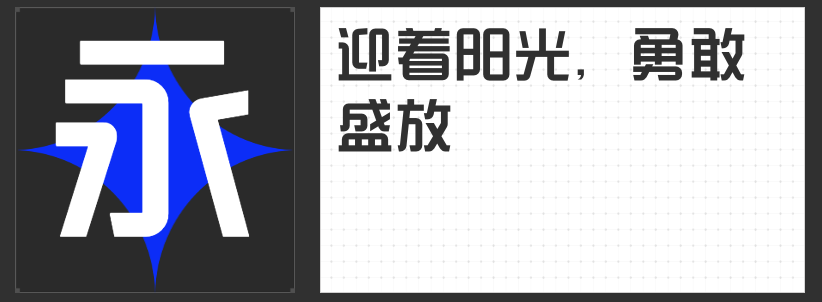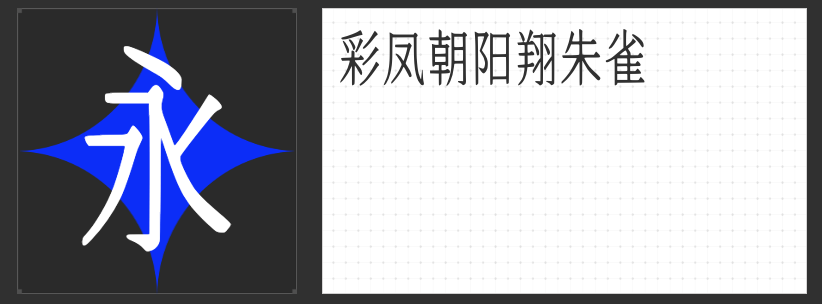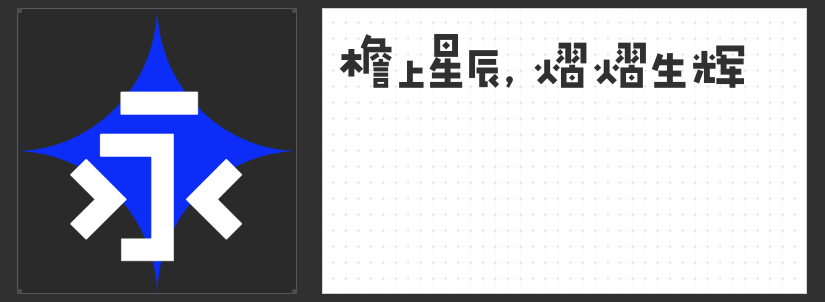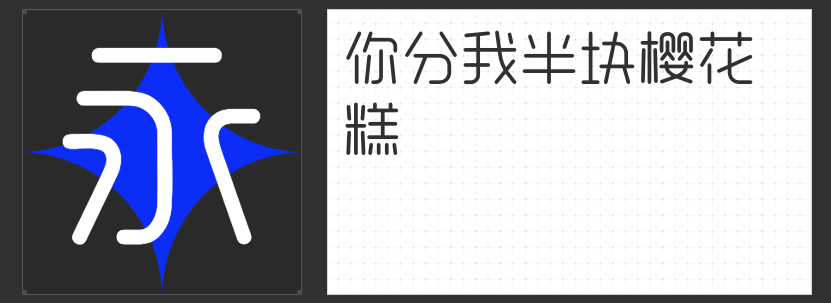
四款创意字体推荐:为现代设计注入独特生命力
在追求视觉冲击力与创意表达的现代设计中,字体的选择往往成为作品成败的关键。以下四款非免费但极具设计价值的字体,凭借独特的风格与工艺,成为设计师提升作品辨识度的利器。
1. 创客贴综艺体常规
这款字体以黑体为基底,通过将笔画转折处处理为圆弧形态,赋予字体柔和的视觉触感。其设计突破传统黑体的生硬线条,在保持易读性的同时,通过圆润的笔画传递出亲切与活力。无论是综艺节目片头、社交媒体海报,还是H5动态页面,这款字体都能以流畅的线条与现代感,快速抓住观众注意力,成为视觉焦点。
2. 创客贴幼稚园体细
作为一款专为可爱风格设计的字体,创客贴幼稚园体细将“圆润”二字发挥到极致。笔画全部采用圆滑处理,中宫宽松、字面大,整体呈现出天真无邪的童趣气质。其无衬线体的结构搭配柔和的弧度,既适合儿童书籍、动漫游戏等场景,也能为母婴品牌、教育机构的设计注入温暖与亲和力,成为传递“萌系”美学的理想选择。
3. 机甲宋朱雀号
这款字体将宋体的传统韵味与机甲元素的未来感完美融合。修长的字形结构搭配刚毅的笔画线条,既保留宋体“横细竖粗”的书法特征,又通过机甲风格的锐利转折与金属质感,营造出强烈的科技冲击力。无论是科幻电影海报、游戏界面,还是科技产品宣传,机甲宋朱雀号都能以独特的视觉语言,传递出“刚柔相济”的矛盾美学,成为打破常规的创新之选。
4. 创客贴星星体
创客贴星星体以“横平竖直”的几何结构为基础,通过将点笔画设计为菱形,打破传统字体的比例规则,赋予字体灵动俏皮的视觉张力。其字形大小不一、错落有致,仿佛夜空中闪烁的繁星,为设计注入童趣与梦幻感。这款字体尤其适合儿童品牌、节日活动或年轻化产品的视觉呈现,以不规则的布局与跳跃的节奏,传递出轻松愉悦的氛围。
四款字体各具特色,从圆润灵动到刚柔并济,从童趣美学到俏皮灵动,它们以独特的设计语言,为现代设计提供了丰富的表达维度。无论是追求视觉冲击力,还是传递情感温度,这些字体都能成为设计师手中的“创意武器”,助力作品脱颖而出。